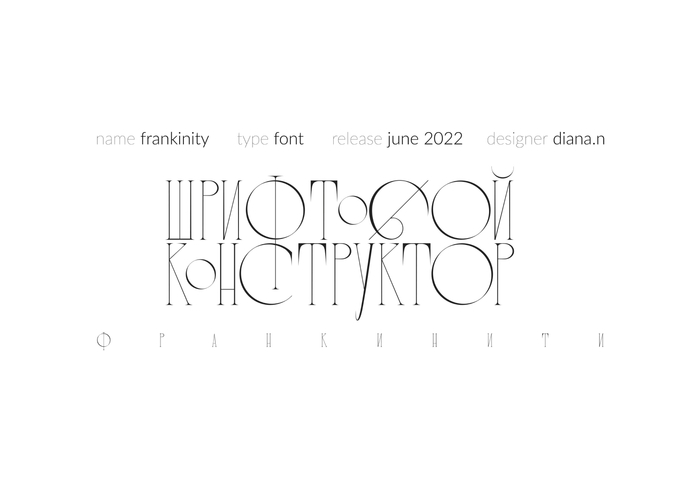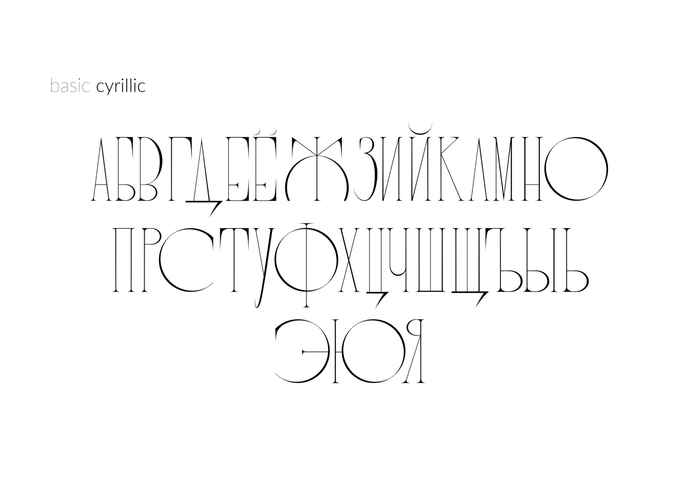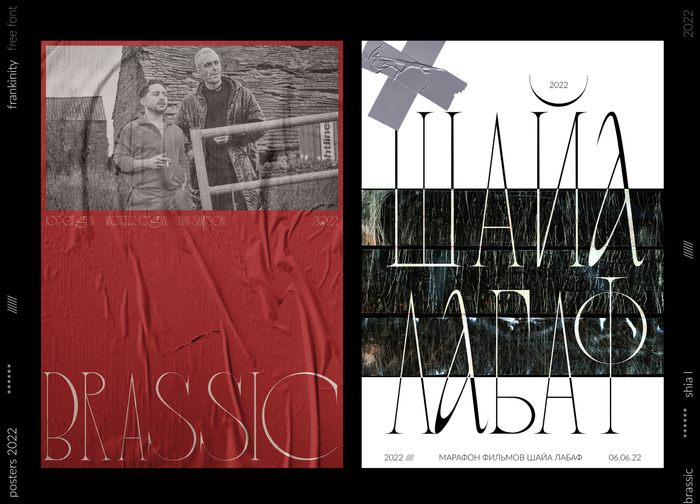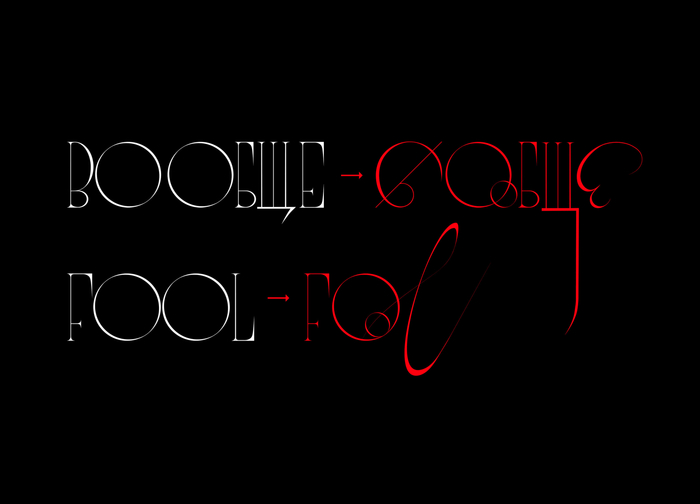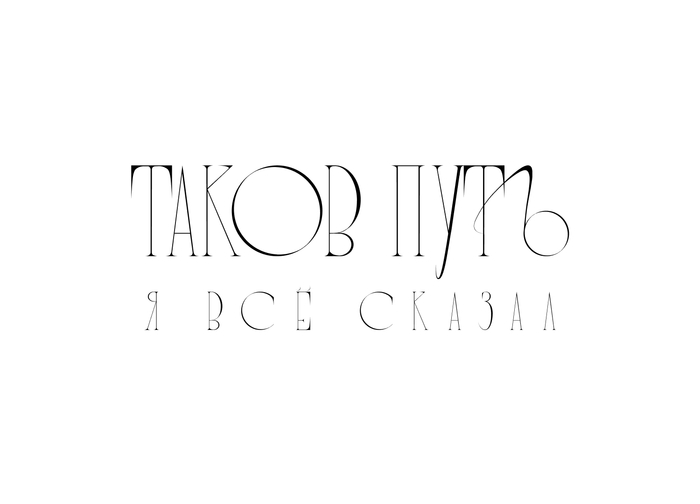
Шрифт FRANKINITY. Бесплатный
Откровенность. Так переводится название этого изящного шрифта. Читаемостью он похвастаться не может. Но зато как красиво соединяются в нем буквы. Лигатура нравится. В каком-нибудь постере я бы точно использовал. К тому же автор расщедрился. Шрифт бесплатен для коммерческого использования) Автор: Diana N